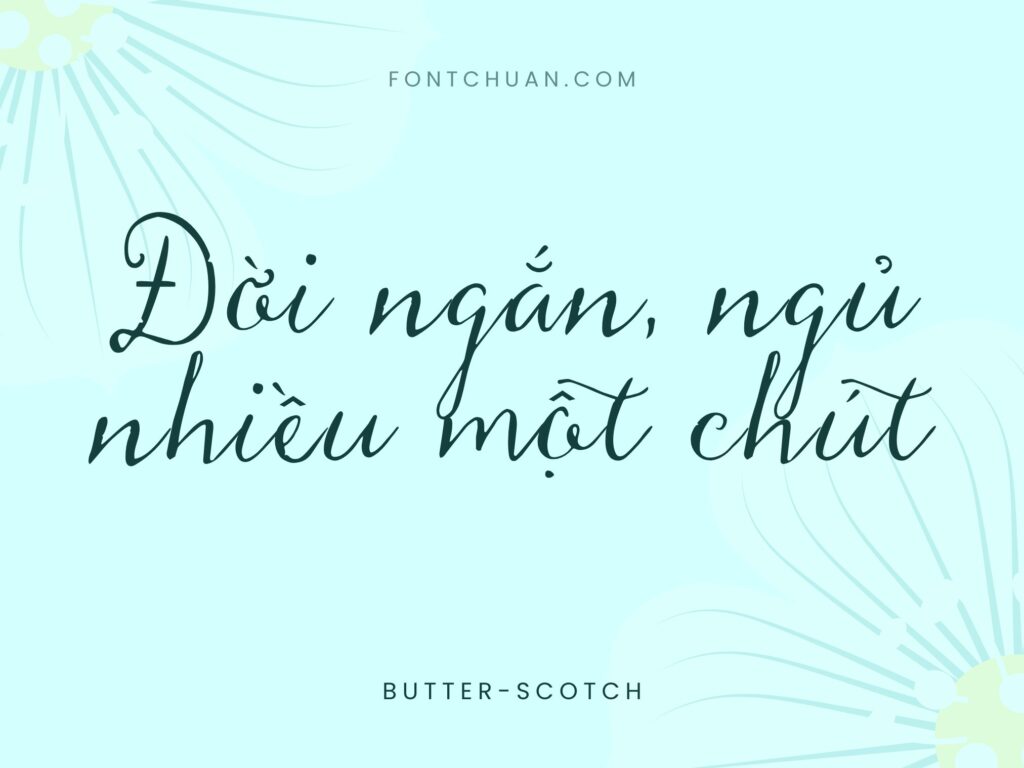
Font iCiel Butterscotch Việt Hóa
Butterscotch là một kiểu chữ viết tay độc đáo được thiết kế bởi Graphix Line Studio. Font này mang phong cách thủ công, với các ký tự mềm mại và tự nhiên, tạo cảm giác gần gũi và thân thiện. Đặc biệt, Butterscotch hỗ trợ tiếng Việt và nhiều ngôn ngữ khác, đáp ứng nhu cầu đa dạng của người dùng. Thành viên của Font Chuẩn đã sưu tầm và chia sẻ font này, giúp cộng đồng thiết kế ứng dụng dễ dàng trong các dự án của mình.
Về đặc điểm thiết kế, Butterscotch sở hữu các ký tự viết tay tinh tế, với đường nét mượt mà và uyển chuyển. Font này phù hợp cho các thiết kế như thiệp mời, logo, bao bì sản phẩm, và các ấn phẩm truyền thông xã hội. Ngoài ra, Butterscotch còn thích hợp cho các ngành nghề như ẩm thực, quảng cáo, thiệp cưới và spa, cùng các sự kiện đặc biệt như lễ hội, sinh nhật, Valentine, Trung thu.